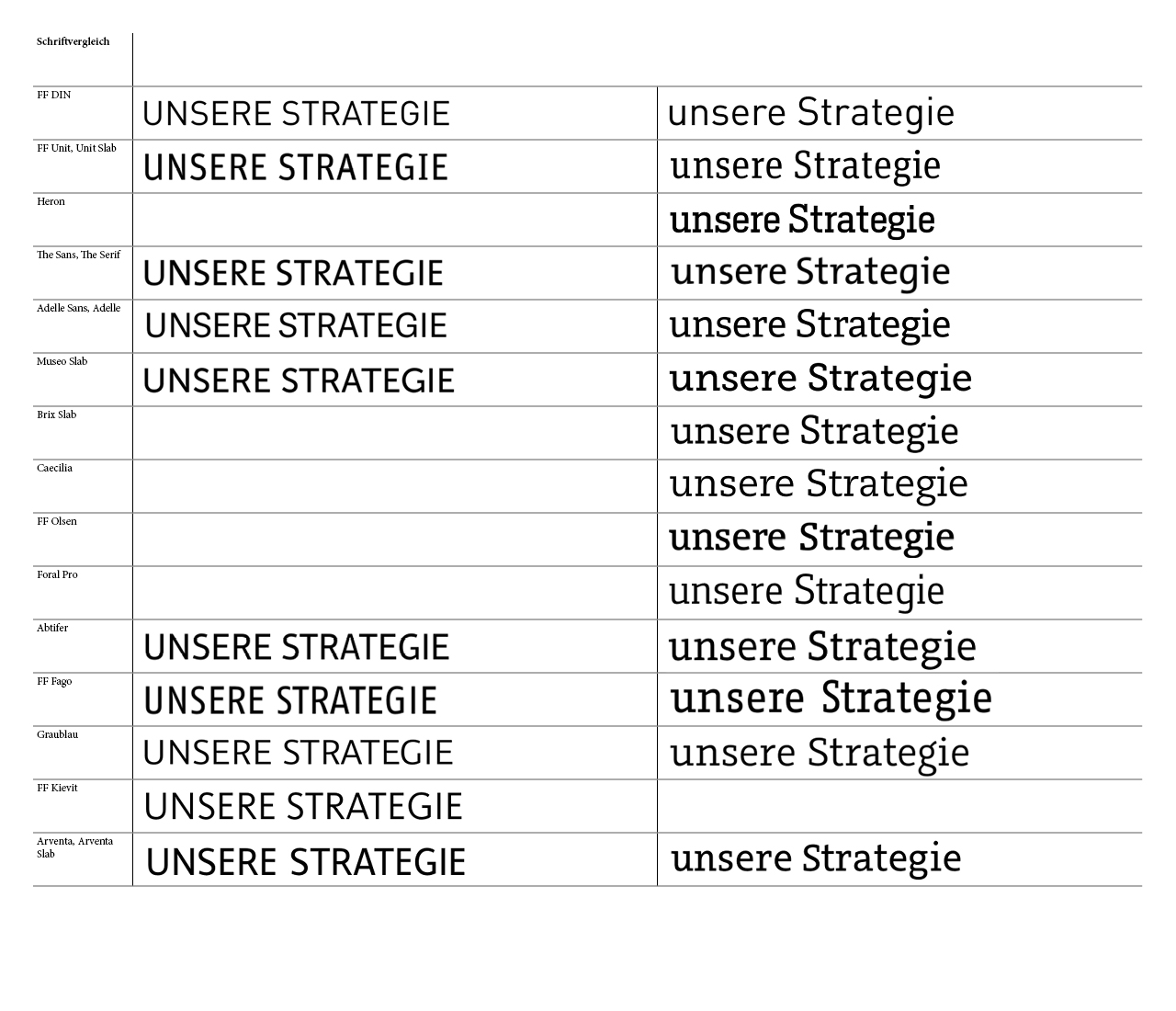
Schrift(sippe) gesucht
Ich plane gerade ein größeres Projekt, wofür ich eine Schrift(sippe) bzw. eine Textschrift suche.
Hier ein paar Fakten:
- Die "Hausschrift" ist die DIN
- Ich suche eine passende Serifen Schrift oder eine Schriftsippe, bei der die Grotesk der DIN ähnelt
- als Serifenschrift würde ich eine Slab Serif bevorzugen, da das Unternehmen sehr modern und lifestyleorientiert ist
- die Schrift(sippe) muss sehr gut ausgebaut sein (Tabellenziffern, Kapitälchen, Ligaturen etc. etc.)
Ich habe hier etwas recherchiert, aber bin noch zu keinem guten Ergebnis gekommen... in einem anderen Post wurde z.B. die Caecilia vorgeschlagen, welche aber nicht soo optimal passt, finde ich. Die bekannten Sippen habe ich probiert, aber wirklich ähnlich ist der DIN da keine leider.
Ich erstelle morgen mal eine Übersicht, aber die Adelle geht in die richtige Richtung finde ich (sehr ähnliche Buchstabenformen, wenig Strichstärkenunterschied, eher statisch, aber trotzdem eine gewisse Dynamik ...)
Hier mal eine erste Übersicht...
Adelle find ich gut, Museo find ich auch stark (hat die schonmal wer im Einsatz gehabt?), Abtifer kommt in die engere Auswahl, Graublau find ich stark (Schade, dass das G so blöd ist), Arventa ist auch nicht schlecht!
Eine Sippe wäre mir letztendlich wohl lieber als eine Serifenschrift zur DIN!
Wenn es Dir tatsächlich um eine DIN-ähnliche Anmutung geht, fänd’ ich Museo zu breit und rund.
Ansonsten bin ich auch mehr der Sippenverfechter. Dann aber DIN ganz raus, oder?
Bzgl. Graublau: vielleicht fragst Du mal den Forumchef, ob er Dir noch ein g-Alternative für die Graublau organisieren kann. ;-)   Find’s auch schade, dass das so aus der Reihe tanzt. Vielleicht steigert so eine Alternative ja noch mal die Verkaufszahlen.  :-o  ;-)
Adelle find ich gut, Museo find ich auch stark (hat die schonmal wer im Einsatz gehabt?) […]
Die Museo wird so weit ich weiß von DELL in einer überarbeiteten Version eingesetzt.
Da kannst Du ja mal schauen, wie sie bei denen wirkt (ohne wirkliche Ahnung zu haben, finde ich sie sehr breit laufend)
Ja, sie läuft leider sehr breit und fällt aus diesem Grund raus!